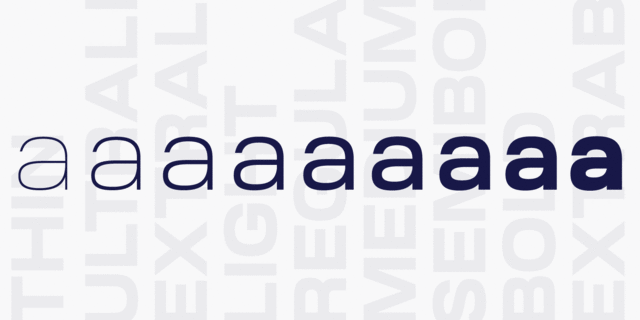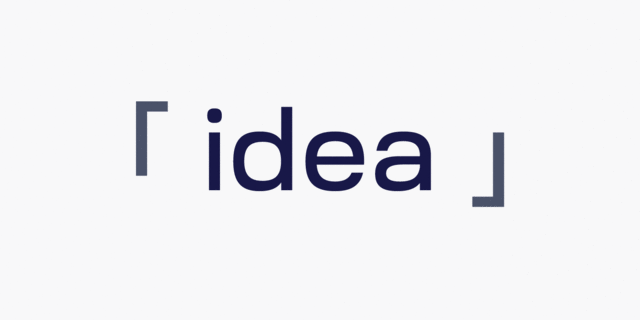
Геометрический гротеск со спрямленными овалами, напоминающий итальянские шрифты 1950-х и 1960-х годов, но имеющий значительно более округлые формы, чтобы придать ему более современный вид. Шрифт поставляется в 9 насыщенностях с сопутствующими наклонными начертаниями и поддерживает латиницу, греческий и кириллицу. Шрифт разработал Олег Лищук в 2020 году.